写真整理用マンスリーカード ブロック玩具フォント
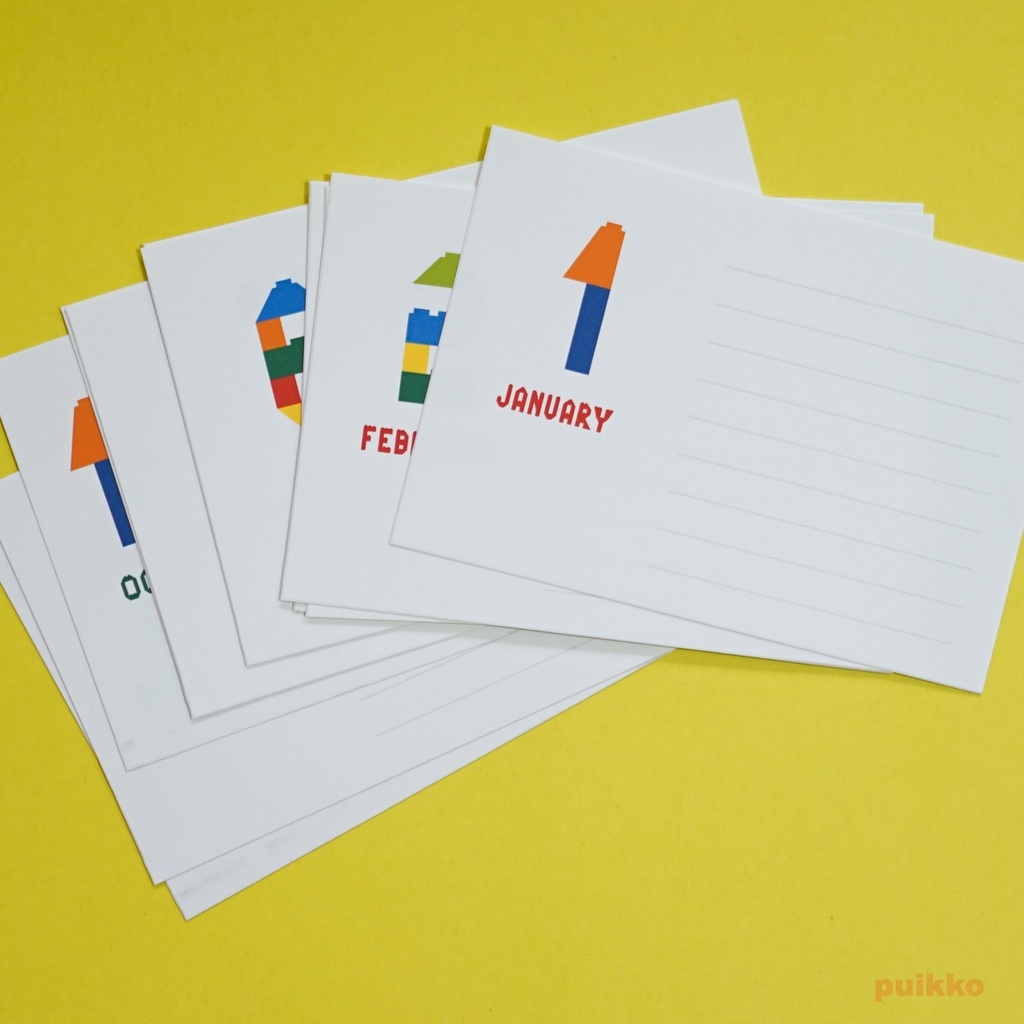
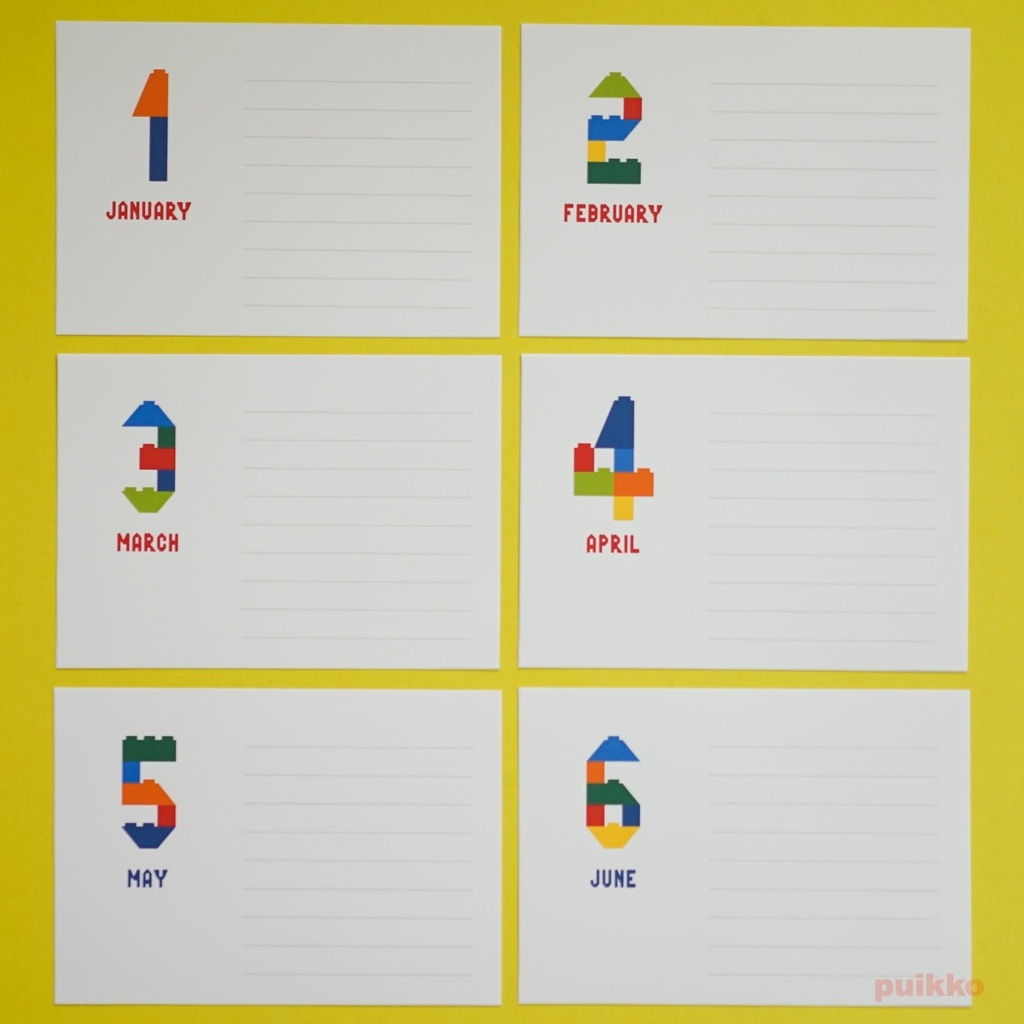
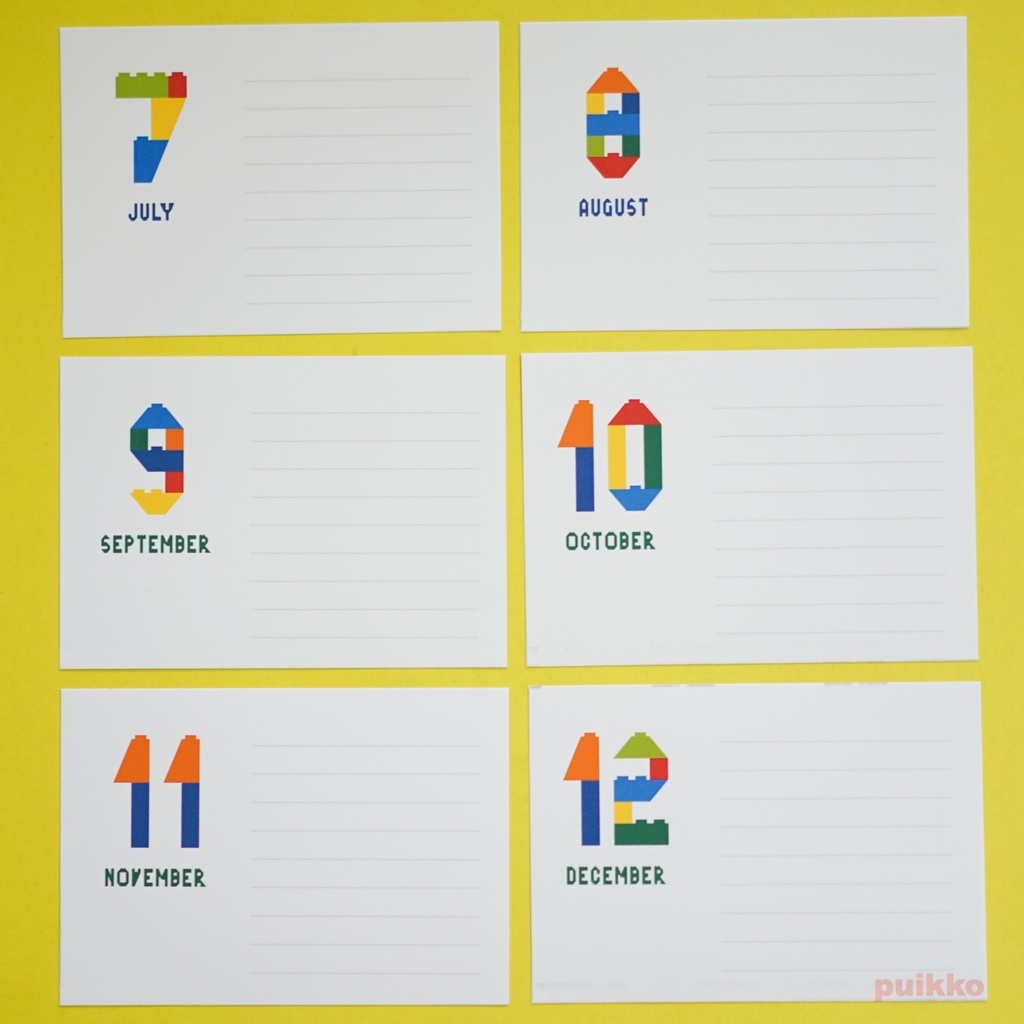
写真整理用のマンスリーカード12枚セットです。 1か月ごとに、写真アルバムに差し込んでお使いください。空きスペースにメモを書くこともできます。 組み立てブロックを組み合わせて作ったイメージの数字とアルファベットの自作フォントのカードです。 L判の写真と同じサイズなので、ポケットアルバムなどでL判の写真を整理するのに役立ちます。 【素材】 マット紙・厚口 厚さ0.17mm 【サイズ】 幅127×高さ89mm(L判)×12枚 【購入の際の注意点】 写真と実物では多少色味が異なる場合があります。 インクジェットプリンタを使って市販の用紙に印刷し、カットしているので、精密さに欠けるところがあります。あらかじめご了承ください。 防水されていませんので紙濡れにご注意ください。